今回は、人気の和風デザインフォントをなんと40書体も収録した「和風デザインフォントコレクション」です。
「和風デザインフォントコレクション」の気になる中身
基本筆文字14書体
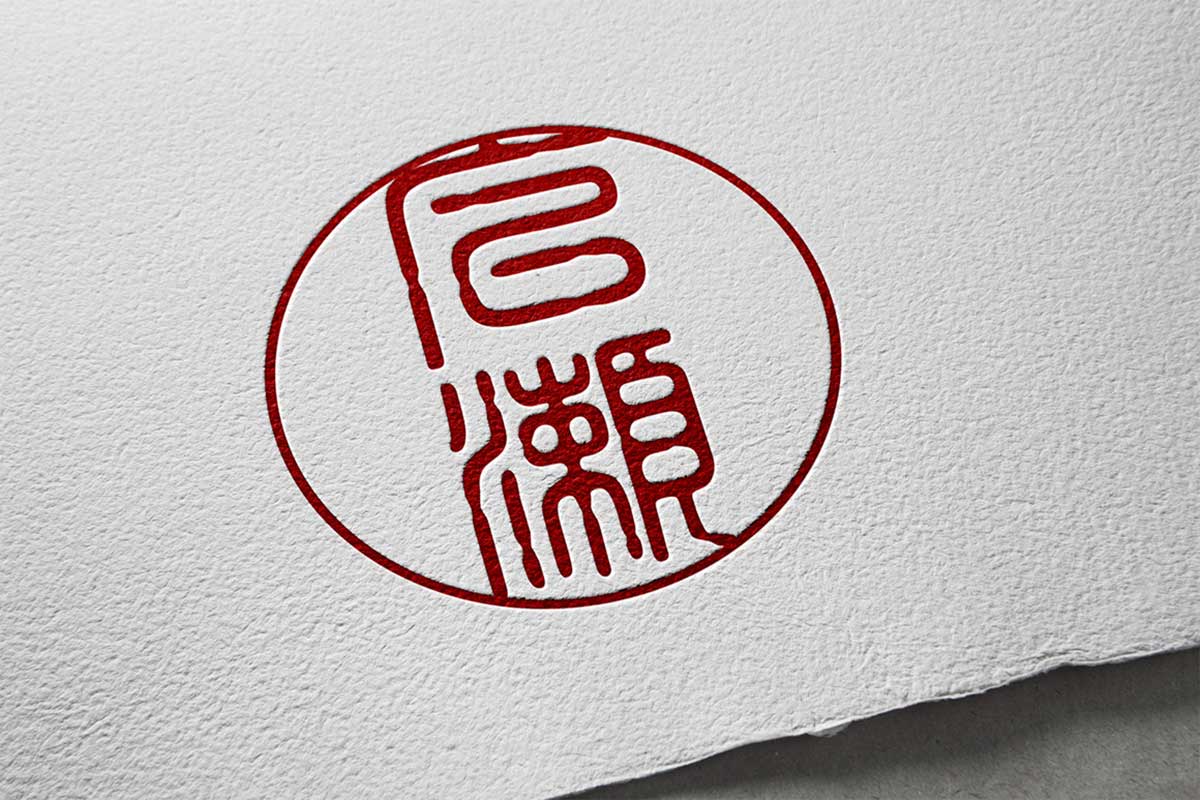
シンプルで使いやすい書体が中心の基本筆文字。個人的には、あまり使わないけどあるとうれしい印鑑のような篆書(てんしょ)体が入っているのがポイント高いです。
- セイビタカナワB/L/M/UB
- セイビシバB/M/UB
- セイビミタM
- セイビ正隷書体B/M
- セイビ宋朝体
- 大和楷書
- 大和篆書
- GMAP行書B
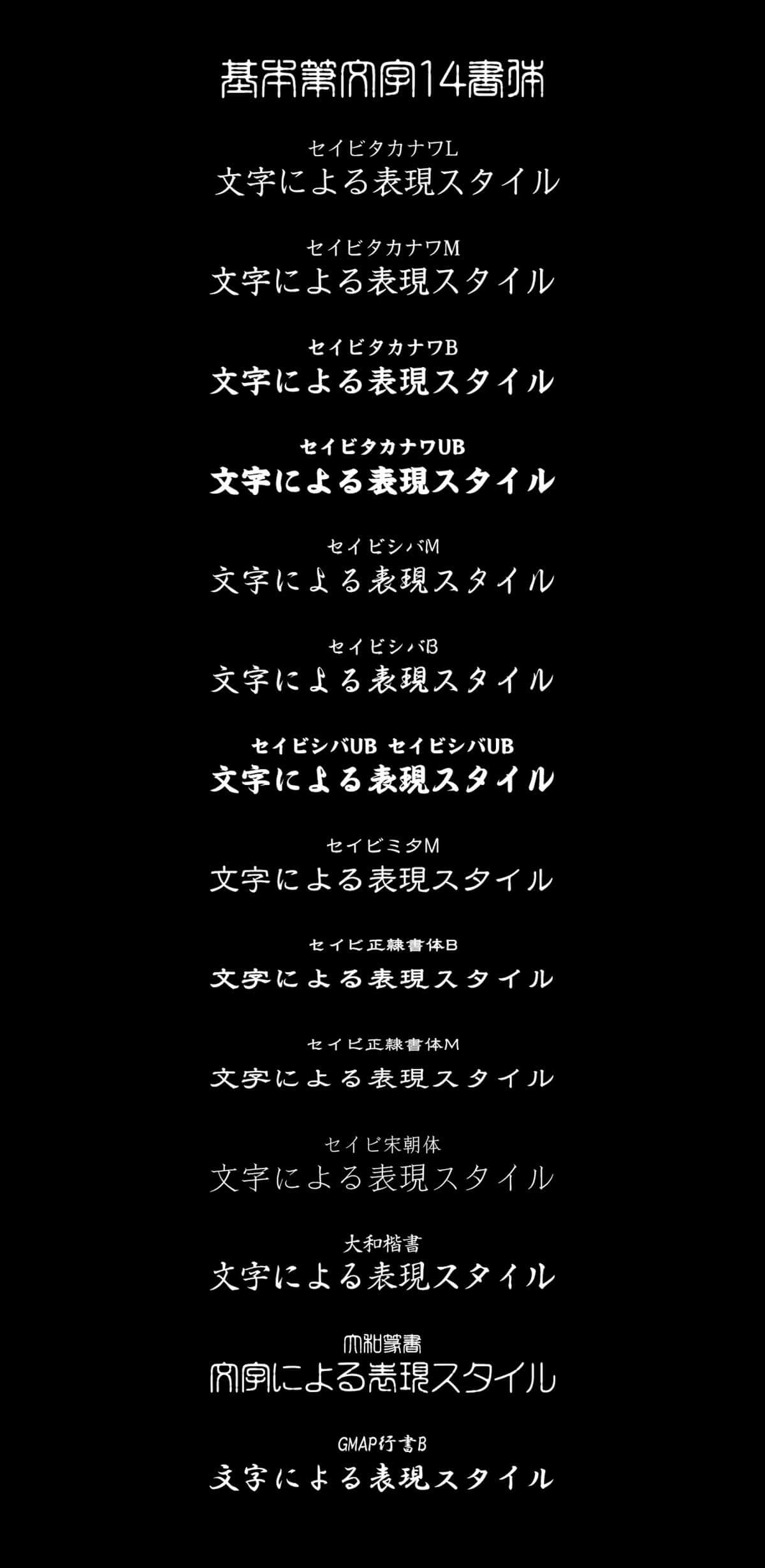
和風デザイン11書体
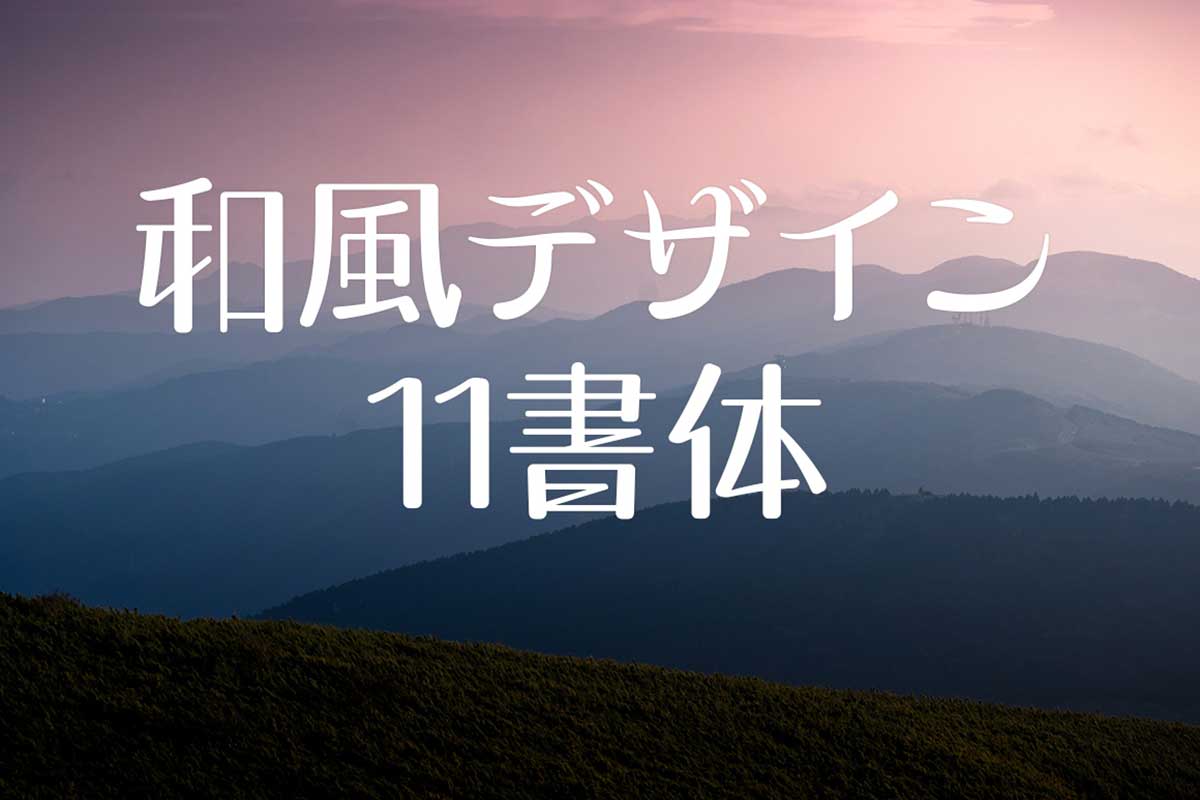
デザインカッツで今まであまりなかった、女性向けや子供向けの媒体にぴったりのデザイン書体。持っておけばなにかと便利に使えること間違いなしです。
- 雛-old-M
- 雛-old-B
- 和楽-Medium
- 和楽丸-Medium
- 喜楽-Medium
- 雅楽-Medium
- 雅楽丸-Medium
- かるた-Regu
- かるた丸-Medium
- 駿河-Medium
- 駿河丸-Medium
江戸文字7書体
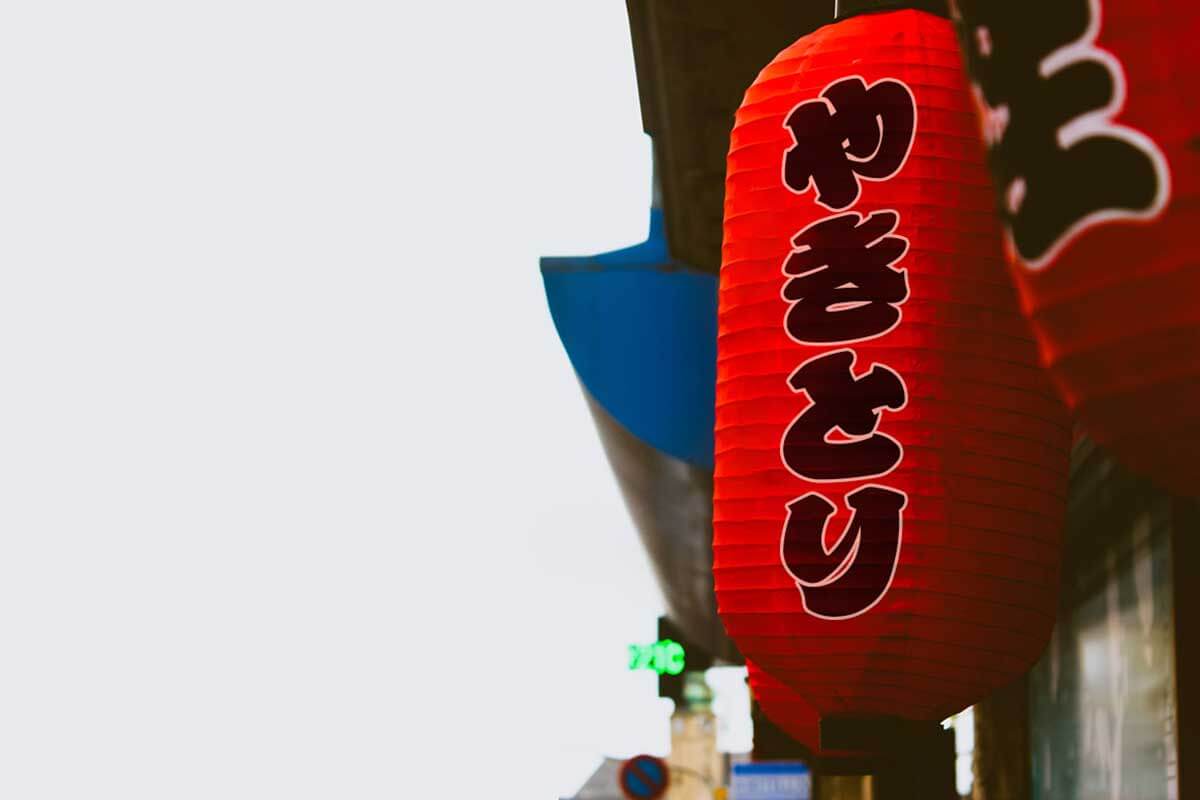
- GMAPひげ文字U
- GMAP古印体EB
- GMAP相撲文字H
- GMAP俵H
- GSNPひげ文字EB
- GSNP演芸EB
- GSNP勘亭流EB
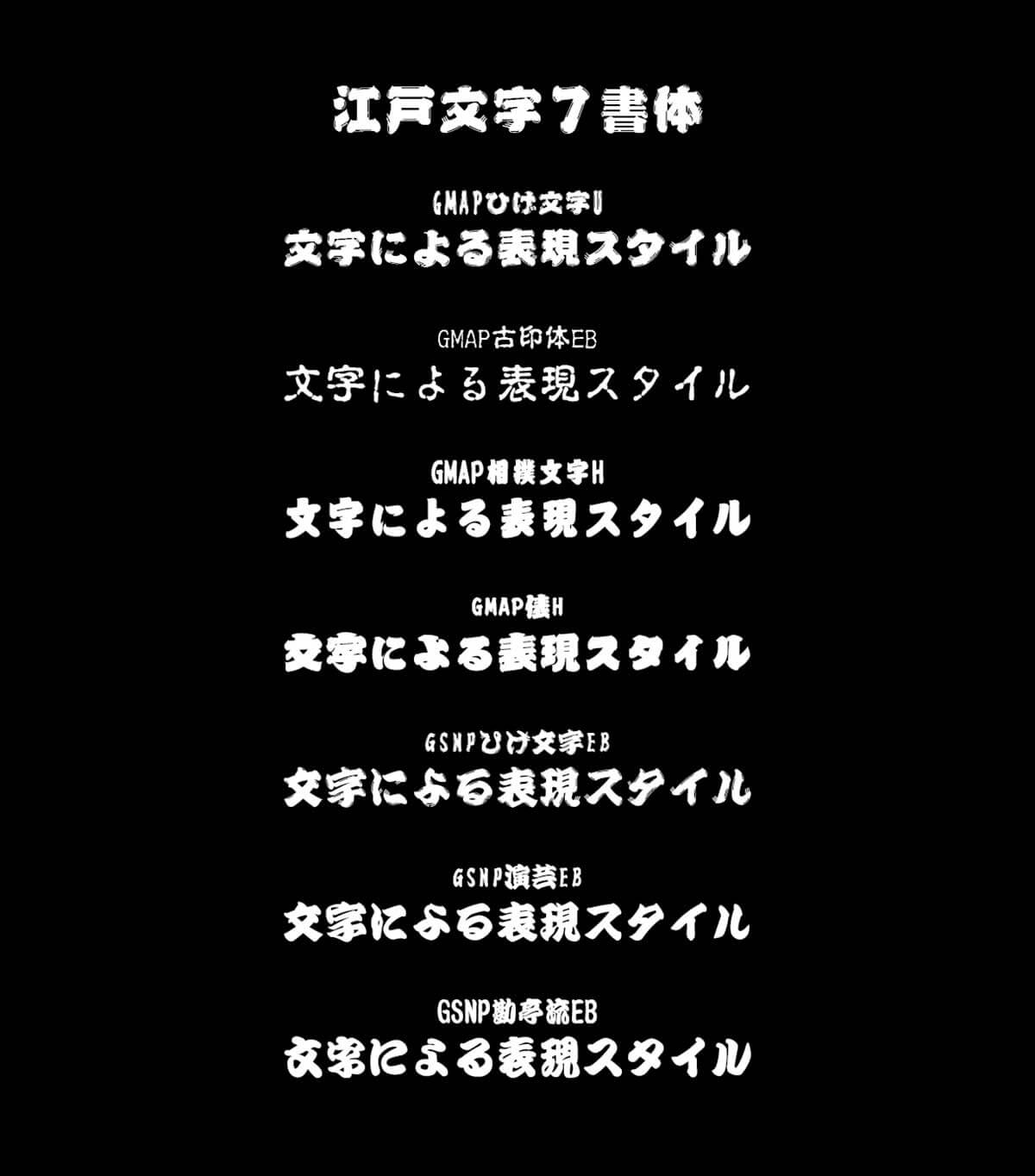
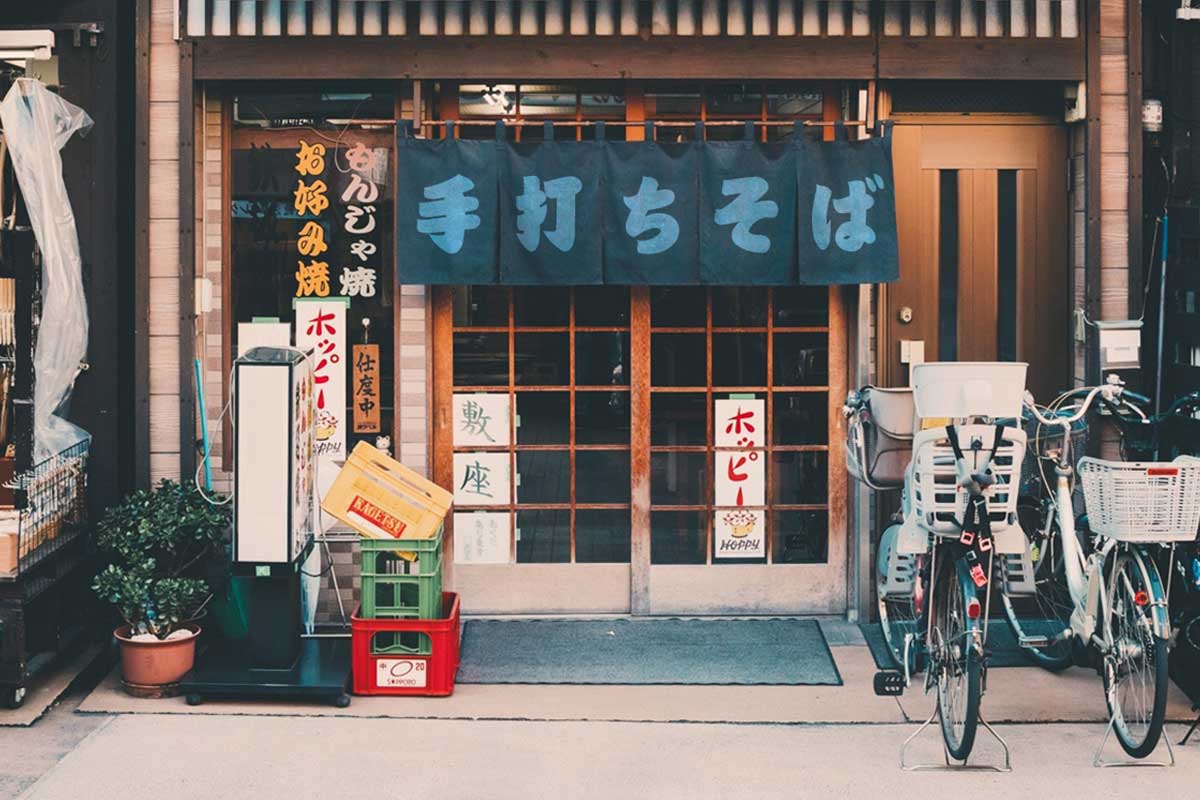
デザイン筆文字8書体
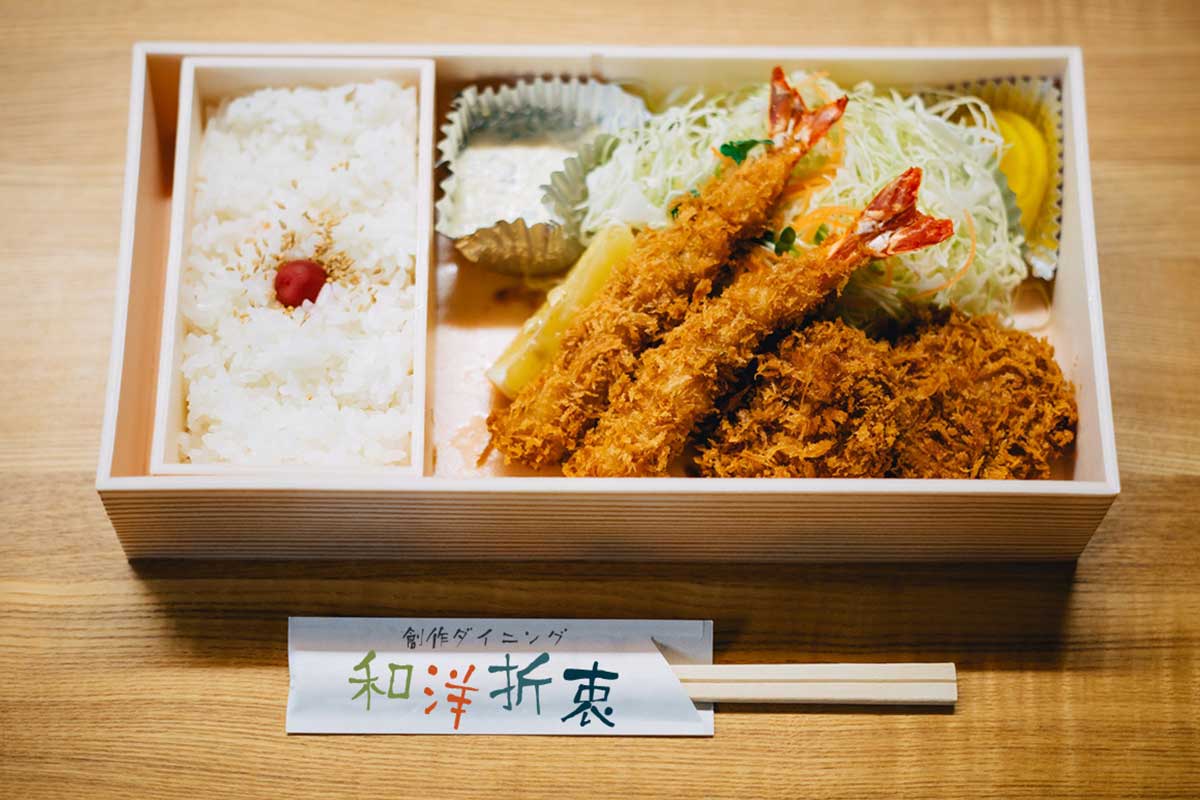
ちょっとくずした表現がおしゃれなデザイン筆文字。和風でも今どきな雰囲気を演出したいときに便利な書体がそろっています。
- あったか毛筆
- すっきり楷書
- デザイン毛筆
- 美し行書
- 味わい毛筆
- 五風十雨
- いぶき M
- すみれ M